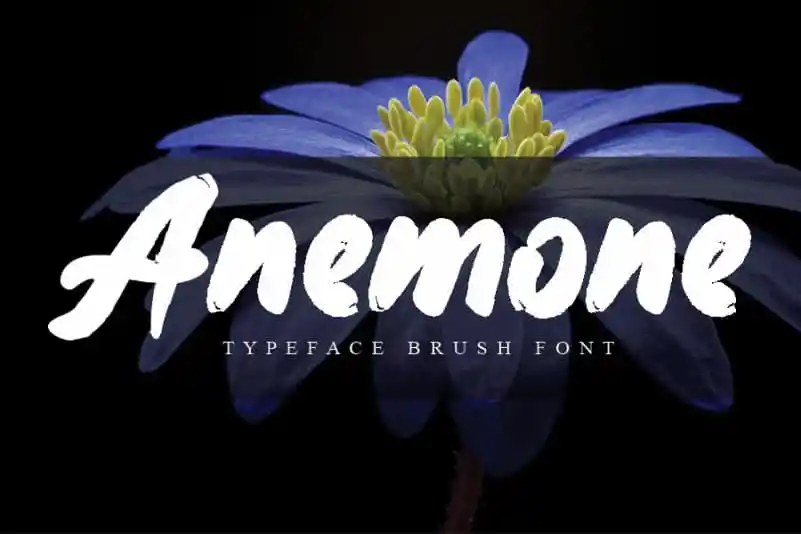
Anemone Brush Font é uma elegante fuente com traços levemente embaciados perfeita para quem busca dar vida a seus projetos criativos. Esta fuente bold e desenhada em branco não só adicionará um toque de modernidade, mas também destaca sua visão única e personalizada. Foi desenvolvida pelo talentoso designer andikastudio, que nos oferece uma opção versátil para expressar suas ideias com criatividade e originalidade. Adicione a Anemone Brush Font aos seus projetos e garanta que eles chamem a atenção dos olhos ao redor. Esta fuente brilhará em qualquer aplicação, seja ela um design gráfico, uma publicação de mídia social ou até mesmo um projeto de arte digital. A Anemone Brush Font é a escolha perfeita para quem busca personalidade e destaque em cada trabalho que faz.